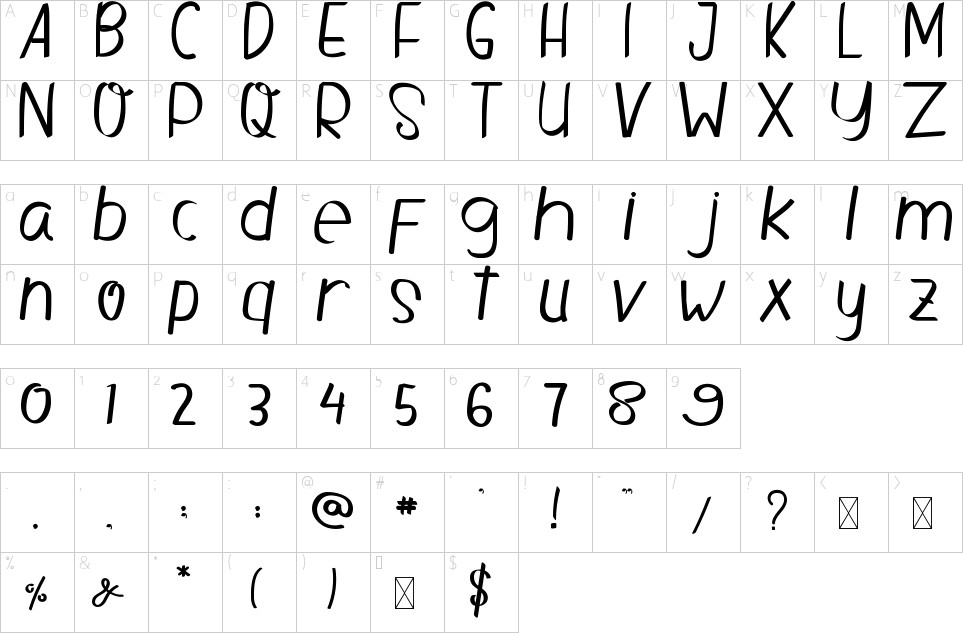
Descubra a elegância e sofisticação da Grammys Style Font, uma opção única para adicionar personalidade ao seu design no Windows ou Mac. Desenhada pela InermediaSTUDIO, essa fonte representa perfeitamente a atmosfera vibrante e arrojada do Grammy Awards. Gratificantes como você, desejamos oferecer recursos que não apenas aumentam sua produtividade, mas também adicionam uma personalidade única ao seu trabalho. A Grammys Style Font é um exemplo disso, com um design elegante e sofisticado que pode adicionar um toque de glamour a qualquer projeto visual. Com seus 217 downloads registrados até agora, o grampos-style font se destaca como uma opção versátil para designers digitais em busca de personalidade sem perder a qualidade. Adquira a Grammys Style Font hoje e transforme seu trabalho em algo ainda mais especial.